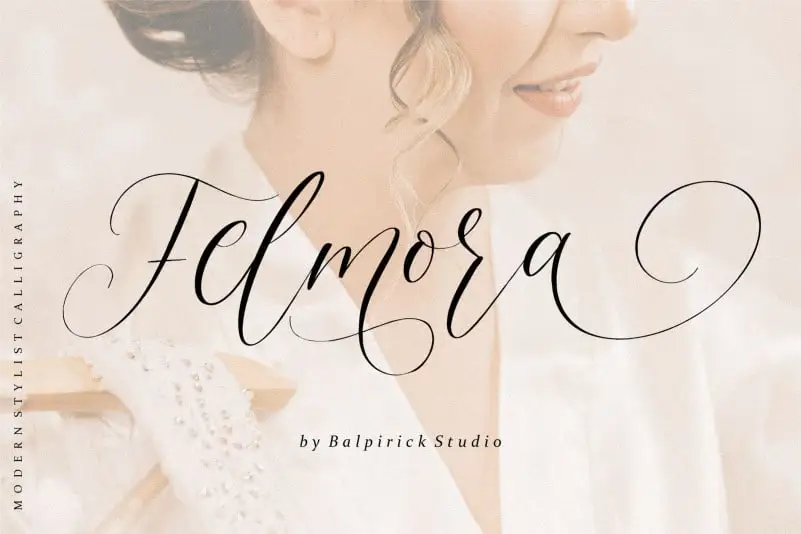
Felmora Calligraphy Font – Download Grátis
A Felmora Calligraphy Font é perfeita para se destacar em qualquer projeto que você realize, seja ele uma embalagem de produto, criação de marca, revista ou até mesmo um post na redes sociais. Seu formato elegante e detalhado permite que você transmita seu estilo de maneira única e sofisticada. A Felmora é ideal para expressar frases sobre o fundo em uma ocasião especial como casamento, ou simplesmente usar para destacar palavras em background. Esta fonte traz um toque atraente e autêntico que se encaixa perfeitamente com diversas necessidades de design. Com sua designer balpirick ao seu lado, você pode garantir que cada projeto seja único e memorável.